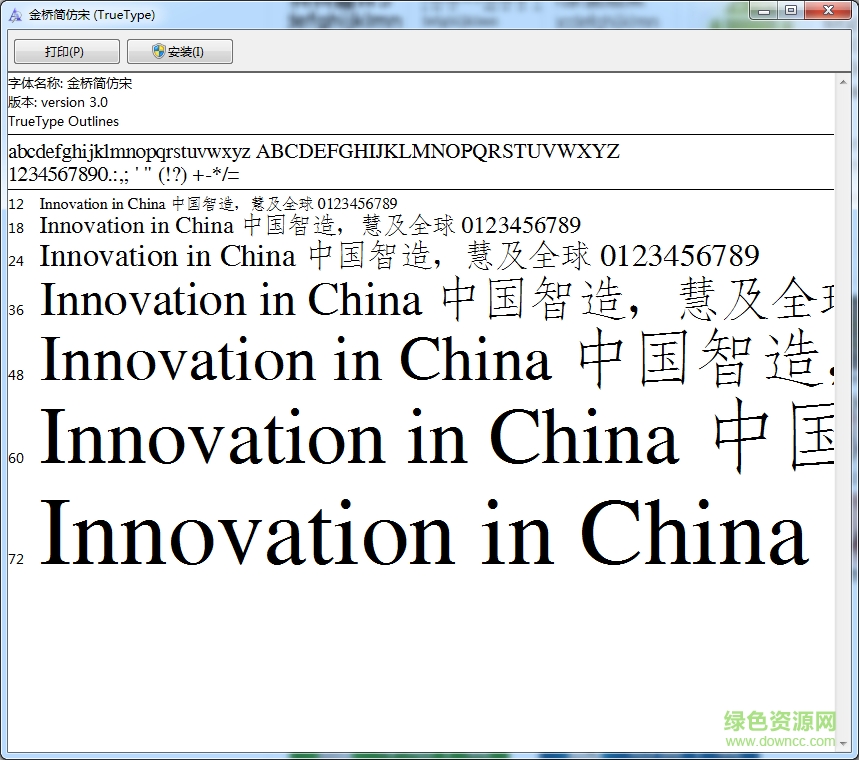
金橋簡(jiǎn)仿宋是一款仿宋類(lèi)金橋字體軟件,字體線(xiàn)線(xiàn)條流暢端正大方,使用起來(lái)也是非常的廣泛,而且在廣告和海報(bào)中使用的非常的多,使用簡(jiǎn)單完全免費(fèi)。快來(lái)綠色資源網(wǎng)下載體驗(yàn)吧!
金橋簡(jiǎn)仿宋是一款字形端正,大方得體的中文簡(jiǎn)體字體,廣泛應(yīng)用于廣告印刷、產(chǎn)品包裝、平面設(shè)計(jì)、電視廣告等行業(yè),喜歡的用戶(hù)可下載收藏。